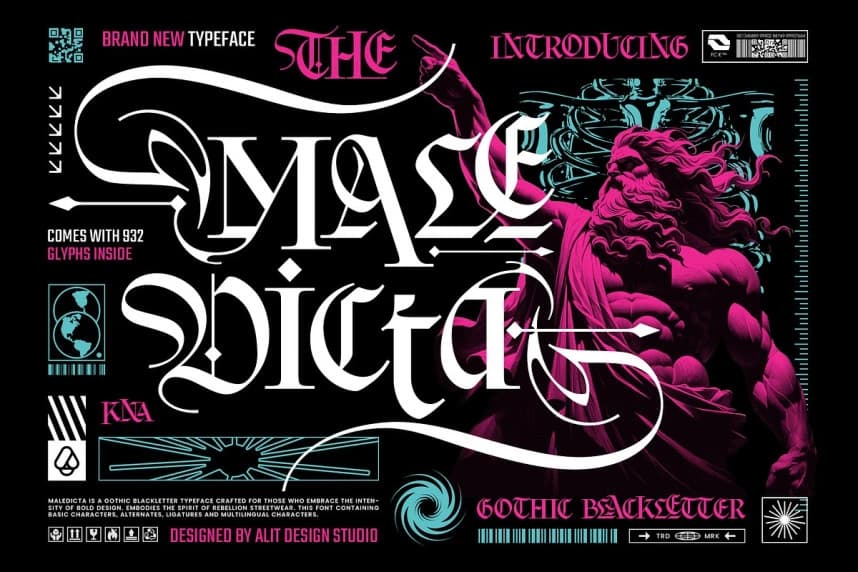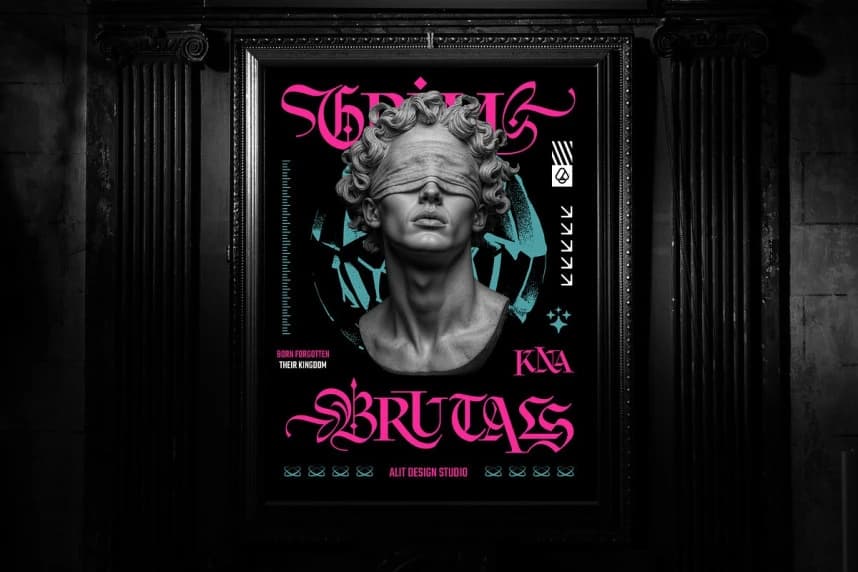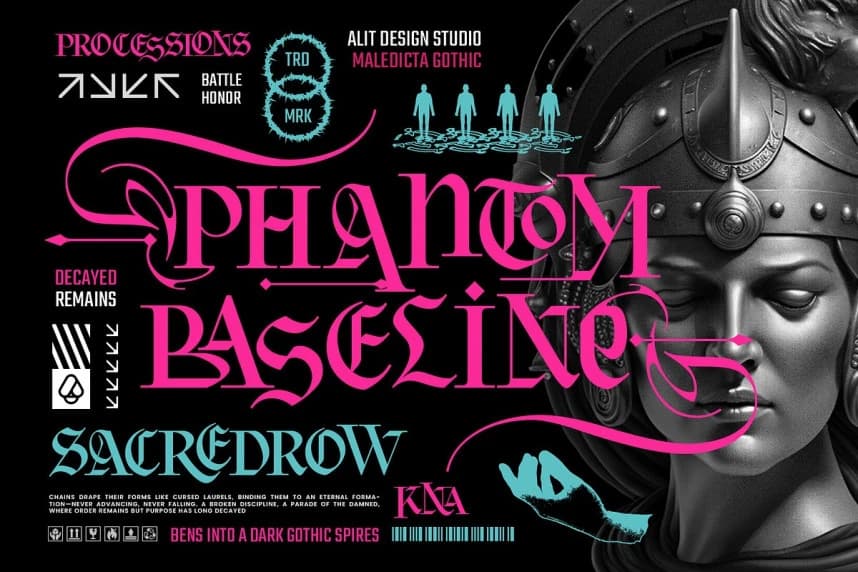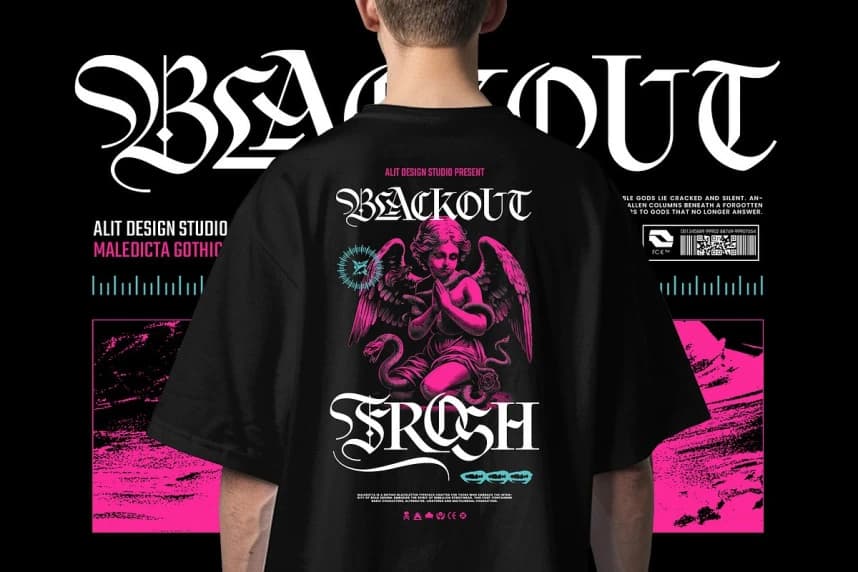
Maledicta Font – Orta Çağ gücüyle modern hassasiyetin cesur bir füzyonu. Maledicta Typeface ile karanlığın ve zarafetin ruhunu serbest bırakın. Klasik Avrupa blackletter kaligrafisinden ilham alınmış ve keskinlikle zenginleştirilmiş.
Maledicta Font – Orta Çağ gücü ile modern hassasiyetin cesur bir birleşimi. Maledicta Typeface ile karanlığın ve zarafetin ruhunu serbest bırakın. Klasik Avrupa blackletter kaligrafisinden esinlenmiş ve keskinlikle zenginleştirilmiş.